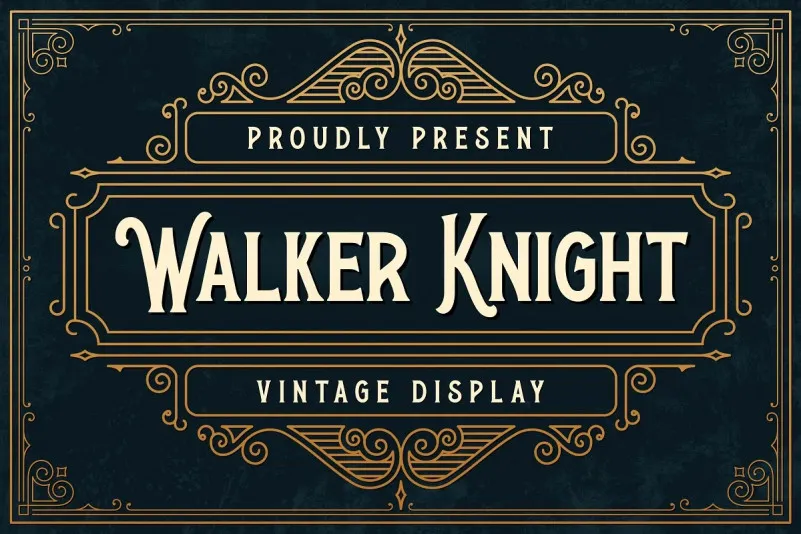
A Walker Knight Font é uma refinada tipografia vintage inspirada no Ironhead serif, desenvolvida para tanto as versões com letra maiúscula quanto minúscula. Esta fonte é especialmente aprimorada e apresenta alternativas de caracteres únicas que garantem um texto fluido e elegante. Ela também se destaca por oferecer suporte multilíngue, tornando-a adequada para uma variedade de aplicativos linguísticos. Inspirada nas artes decorativas e arquitetura dos anos 20, a Walker Knight Font é perfeita tanto para estilos visuais mais tradicionais quanto para os que valorizam o elegante e minimalismo. É uma escolha inteligente para quem busca uma fonte vintage que se destaca por sua sofisticação e versatilidade, ideal para design gráfico e publicações de moda ou arte.